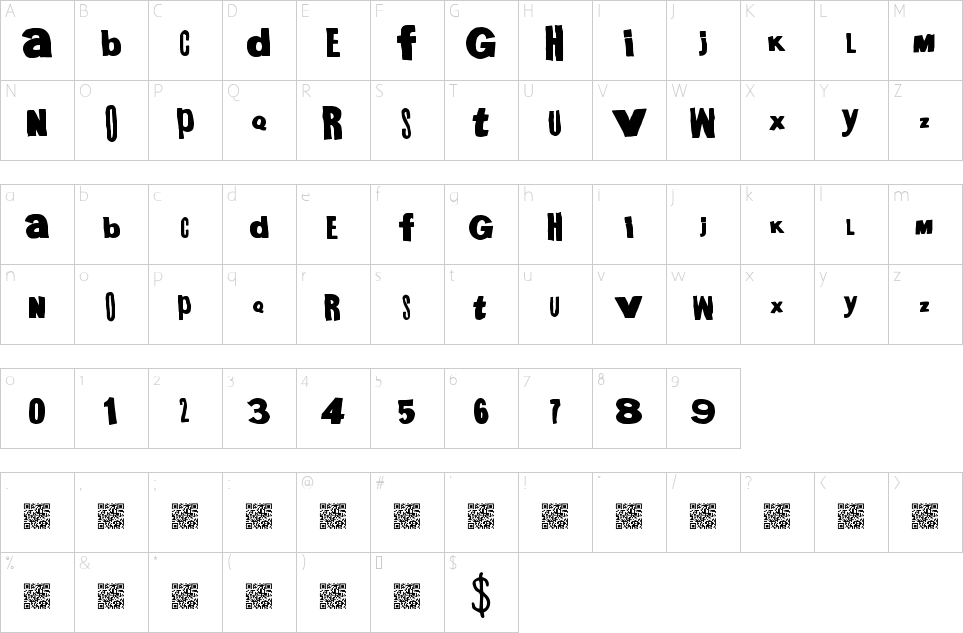
Mega Gothic é uma fonte gothica que adiciona um toque único e inovador a seus projetos digitais. Criada pela equipe visionária da Xerographer Fonts, esta fonte está disponível gratuitamente tanto para Windows quanto para Mac. Com linhas elegantes e um estilo distintivo, Mega Gothic é perfeita para criar um design único e moderno. Essa fonte é ideal para design gráfico, branding, design de sites e qualquer outro projeto onde um toque de elegância e originalidade é desejado. Se você está procurando por uma fonte gothica de alta qualidade sem precisar gastar nada, Mega Gothic é uma escolha excelente. Com seu download fácil, você pode começar a usar a sua nova fonte de imediato. E com uma alta avaliação de mais de dois mil usuários, é fácil ver que essa fonte está recebendo elogios por seu design envolvente e natural.